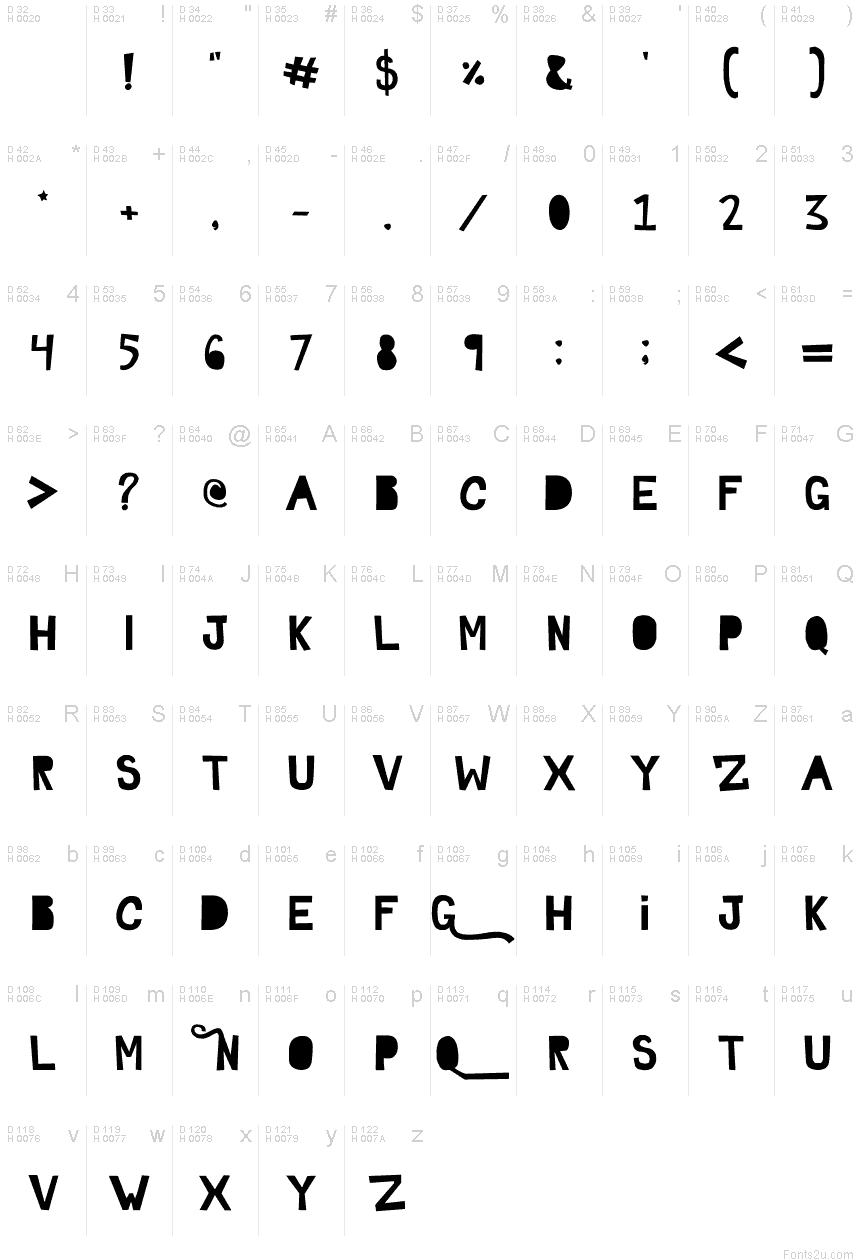
Ghosttown de Andrew Hart es una tipografía display gratuita estilo cartoon, con letras grandes y elásticas que poseen un espíritu travieso dibujado a mano. Las mayúsculas se sienten sueltas y teatrales, con formas redondeadas pesadas, un set ligeramente irregular y ese largo trazo curvo que convierte la palabra en una pequeña pieza de lettering más que en texto corriente.
Encaja a la perfección en títulos de carteles, gráficos para eventos infantiles, packaging con toque de cómic, portadas de fanzines y logotipos cortos donde una fuente gratuita necesita una voz potente y divertida. Úsala para titulares, tarjetas de título o incluso una sola inicial de gran tamaño, porque las letras transmiten tanto movimiento que llenan el espacio por sí solas.